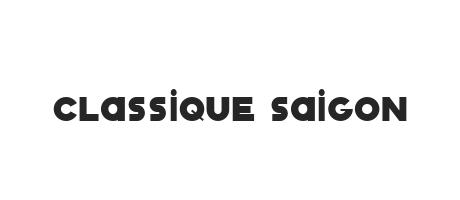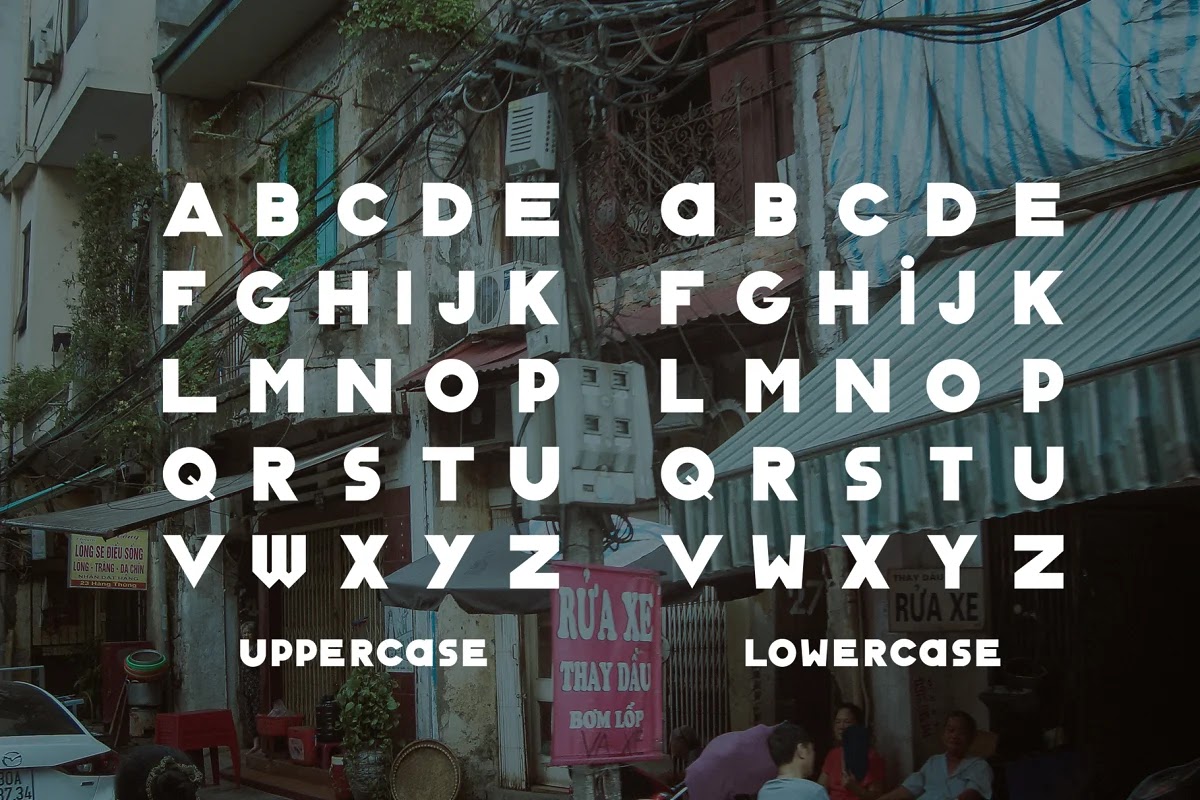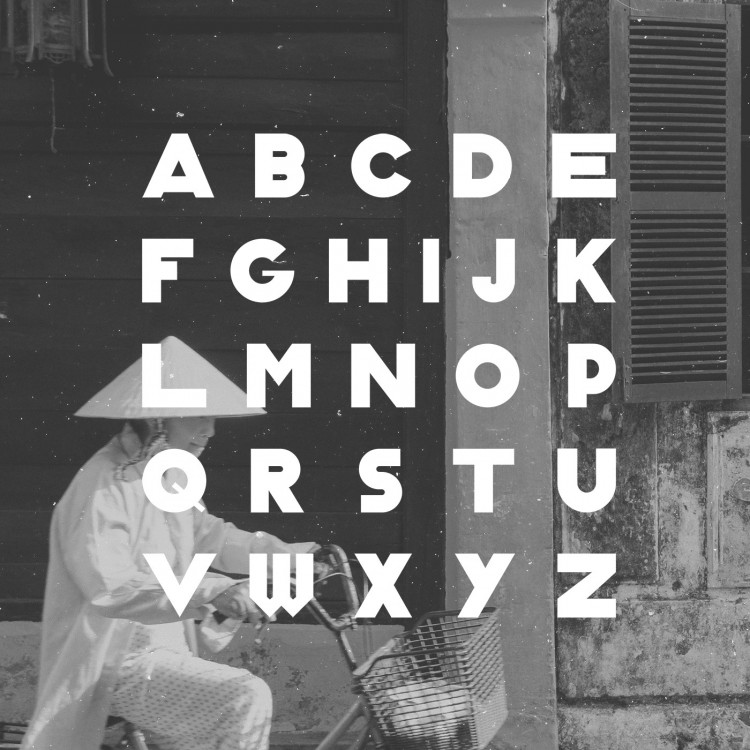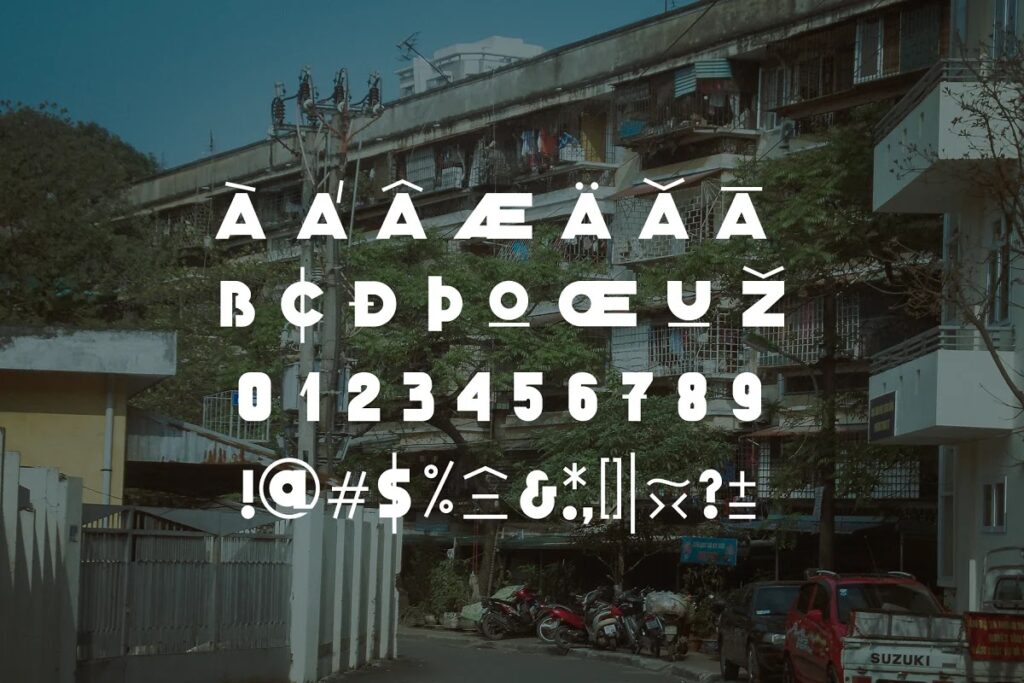
Classique Saigon là một bộ phông chữ mang đậm dấu ấn của hòn ngọc Viễn Đông những thập niên trước, được lấy cảm hứng từ nghệ thuật vẽ bảng hiệu thủ công đầy tính tự sự. Việc sử dụng font Classique Saigon Việt hóa giúp các nhà thiết kế và kiến trúc sư tái hiện lại một không gian văn hóa đặc trưng, tạo nên chiều sâu và sự khác biệt cho các ấn phẩm đồ họa hay phối cảnh kiến trúc.
Đặc trưng ngôn ngữ thiết kế của Classique Saigon Typeface
Điểm lôi cuốn của dòng phông này chính là sự kết hợp giữa cấu trúc hình học chuẩn xác và những đường nét thanh thoát, mô phỏng lại phong cách Typography trên các đường phố Sài Gòn xưa. Classique Saigon typeface sở hữu vẻ ngoài vững chãi, các ký tự được thiết kế với độ tương phản vừa phải, tạo cảm giác thân thuộc và gần gũi. Bản Việt hóa đã xử lý tinh tế hệ thống dấu thanh, giúp các dấu hỏi, ngã, nặng phối hợp hài hòa với khung chữ chính, duy trì nhịp điệu hoài niệm của bộ gốc.
Sự ổn định về mặt thị giác của font Classique Saigon typeface còn nằm ở khả năng gợi mở cảm xúc mạnh mẽ về sự bền vững. Khác với các kiểu chữ in ấn công nghiệp, phông chữ này toát lên vẻ đẹp thủ công tỉ mỉ, rất ăn ý khi phối hợp với các vật liệu truyền thống như gỗ, gạch gốm hay kim loại phủ màu. Đây là phương án hiệu quả để thể hiện cá tính riêng, phù hợp với các dự án homestay, quán cafe hay các văn phòng có tư duy kiến trúc nhân văn và giàu tính bản địa.
| Phân loại phong cách | Retro / Vintage / Display Typeface |
| Mục đích phù hợp | Bảng hiệu hoài cổ, Poster, Logo, Decor nội thất |
Tư vấn trình bày: Để bản thiết kế đạt được hiệu quả thẩm mỹ ổn định, bạn nên sử dụng font Classique Saigon Việt hóa cho các tiêu đề chính hoặc slogan. Việc phối hợp kiểu chữ này cùng một phông không chân (Sans-serif) tối giản cho phần nội dung mô tả sẽ giúp bố cục thông tin trở nên khoa học và chuyên nghiệp hơn.
03 Ứng dụng đưa font Classique Saigon vào thực tế kiến trúc
Nhờ diện mạo giàu tính gợi hình và chiều sâu văn hóa, bộ phông chữ này mang lại giá trị cao trong khâu trang trí và quảng bá các công trình hiện đại:
- Hệ thống nhận diện cho Homestay & Khu nghỉ dưỡng Vintage: Những nét chữ của Classique Saigon rất ăn ý khi xuất hiện trên chất liệu mica gương hoặc gỗ khắc laser tại các khu nhà lắp ghép nghỉ dưỡng. Font chữ này giúp không gian toát lên vẻ ấm cúng và thu hút du khách yêu thích vẻ đẹp xưa cũ.
- Thiết kế Poster và Hồ sơ dự án: Sử dụng tải font Classique Saigon cho tiêu đề các trang hồ sơ năng lực giúp thể hiện tư duy thẩm mỹ sắc sảo, tạo ấn tượng mạnh mẽ về sự chỉn chu của đơn vị thiết kế đối với đối tác và khách hàng.
- Trang trí không gian nội thất Retro: Bạn có thể dùng font này để làm tranh quotes trang trí hoặc uốn đèn neon tại phòng khách nhà lắp ghép nhằm tạo điểm nhấn đầy lôi cuốn và khơi gợi cảm hứng sáng tạo cho không gian sống.
06 Lưu ý để trình bày Classique Saigon Typeface chuẩn thẩm mỹ
Để khai thác hiệu quả vẻ đẹp của dòng font đặc thù này mà không làm rối mắt người xem, người thiết kế nên lưu tâm một số lưu ý kỹ thuật sau:
- Lựa chọn màu sắc mang tính thời đại: Phong cách hoài cổ phát huy hiệu quả thị giác cao khi phối cùng các tông màu như vàng nghệ, cam đất, đỏ bordeaux hoặc xanh rêu đậm. Tránh các màu quá chói lọi làm giảm đi sự sang trọng của bộ chữ.
- Kiểm soát mật độ chữ: Do phông chữ này có cấu trúc nét khá dày, bạn chỉ nên sử dụng cho các tiêu đề ngắn hoặc các cụm từ nhấn mạnh. Việc lạm dụng cho các đoạn văn thuyết minh dài sẽ gây mỏi mắt và làm mất đi trọng tâm của bản thiết kế.
- Nới rộng khoảng cách dòng: Để các dấu tiếng Việt không bị chồng lấn và văn bản giữ được sự minh bạch, bạn nên để khoảng cách dòng thoáng một chút khi trình bày trên các bảng biển hoặc hồ sơ báo giá.